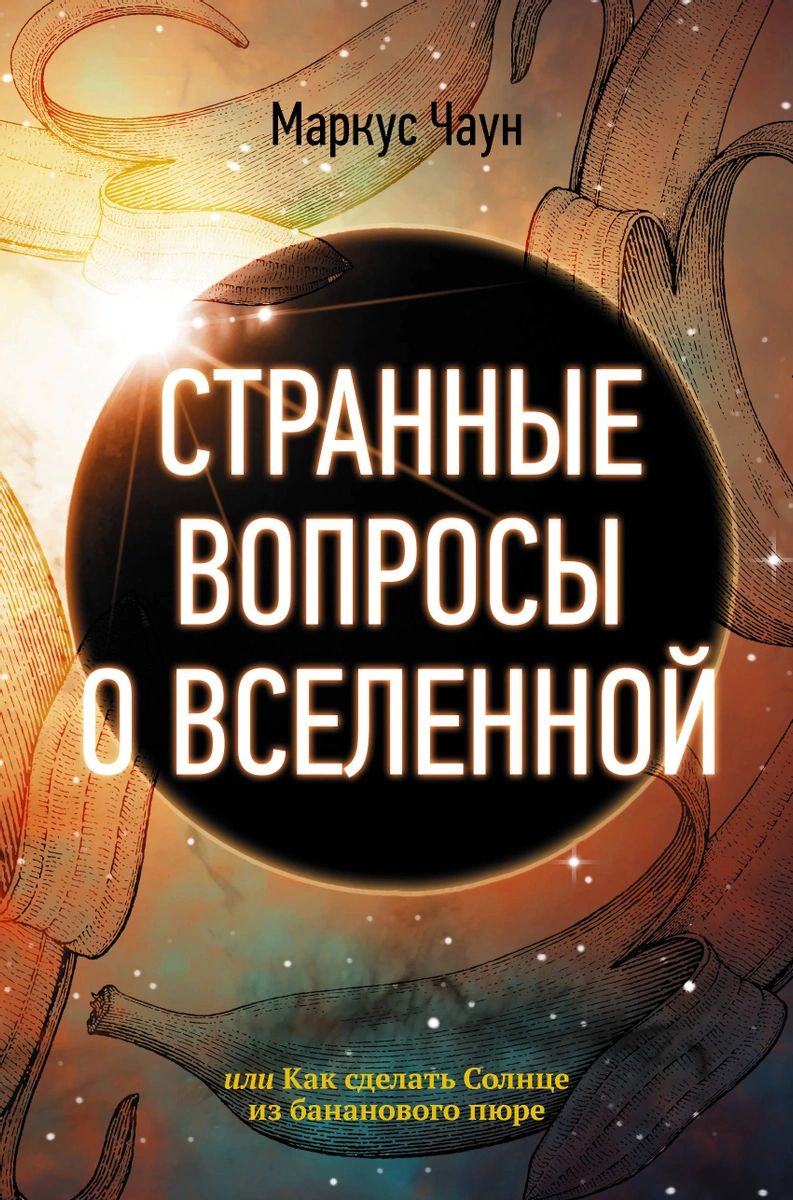
Идеи и советы для использования эффекта золотого шрифта в веб-дизайне
Хотите придать своему тексту элегантный и роскошный вид? Узнайте, как сделать золотой шрифт в несколько простых шагов. Подсказки и идеи помогут вам сделать ваш дизайн ярким и привлекательным.
Используйте специальные шрифты: выберите шрифты с эффектом золота или шрифты, которые имеют глиттерные или металлические текстуры.
Применяйте эффекты текстуры: добавьте блеск или золотистые оттенки к вашему тексту, чтобы сделать его похожим на настоящий золотой материал.
Наложите эффект золотой фольги: используйте специальные стили или фильтры в программе для растровой графики, чтобы придать вашему тексту реалистичный вид золотой фольги.